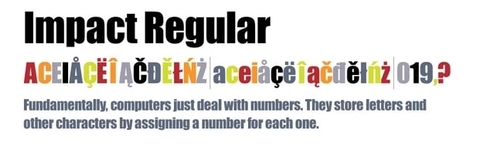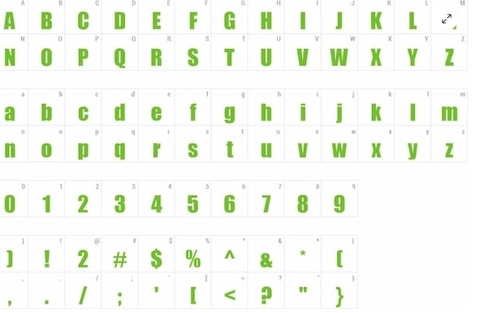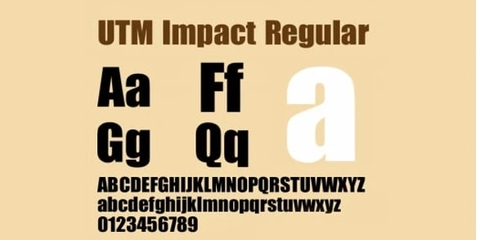
Font chữ UTM Impact
In An Anh chia Sẻ Font Chữ UTM IMPACT Việt hóa tuyệt đẹp dùng cho thiết kế. Font chữ UTM impact được dùng rất nhiều trong thiết kế quảng cáo, thiết kế đồ họa...
Font UTM IMPACT Việt Hóa